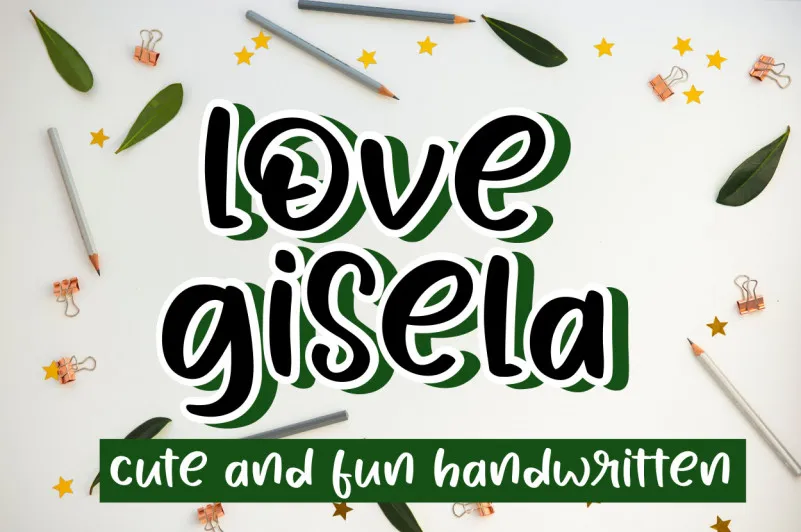
Esta é uma fonte de display única e interessante. Com incrível versatilidade, ela se adapta a uma ampla variedade de projetos. Adoramos seu estilo elegante e moderno, tornando-a perfeita para criar designs impressionantes. Este foi o tipo escolhido por designers que valorizam tanto o aspecto quanto a funcionalidade desta fonte. Ela não só dá um toque sofisticado aos seus projetos, mas também permite uma flexibilidade incrível em sua aplicação. Para qualquer designer procurando por algo novo e chamativo, a Love Gisela Font é certamente um investimento inteligente.